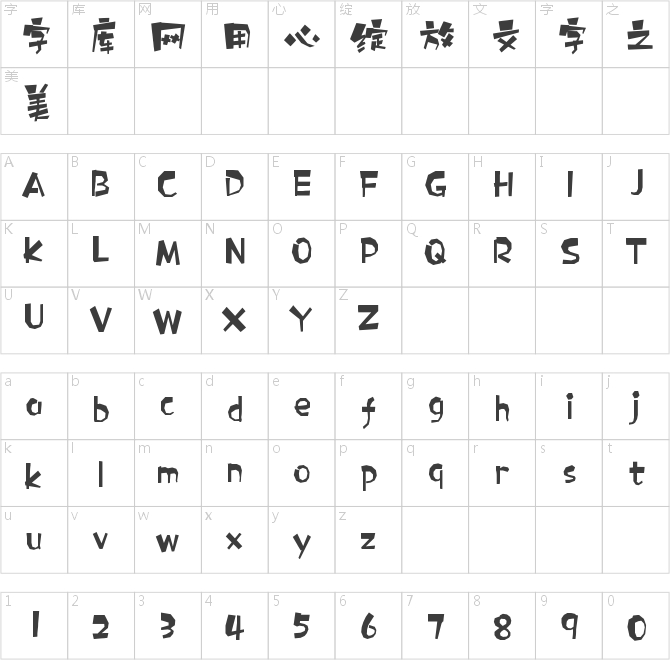
字体名称: 壹心夏日体
壹心夏日体
壹心夏日体介绍
字形特点:
方正中带有动感,棱角分明,以方折构建起字体的框架,活泼生动,辨识度高;
壹心夏日体字体yixinxiariti字库是一款让人赏心悦目、百看不厌的中文字体,适合各类广告和产品包装设计应用,字体大小7.24MB,格式为ttf字体,上传用户是gagilang,作者/版权方为壹心字库